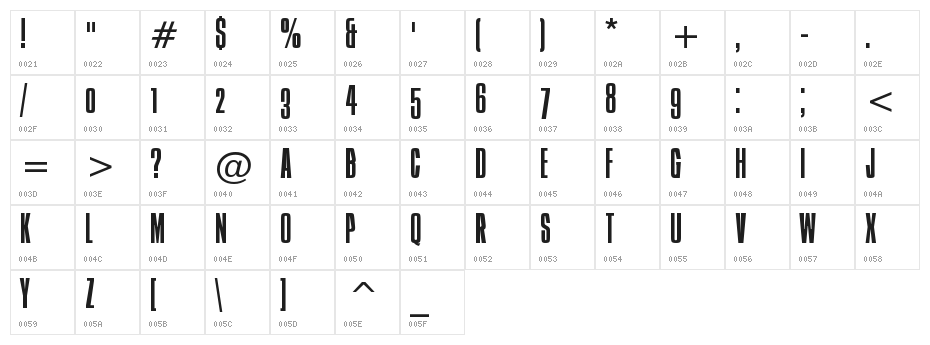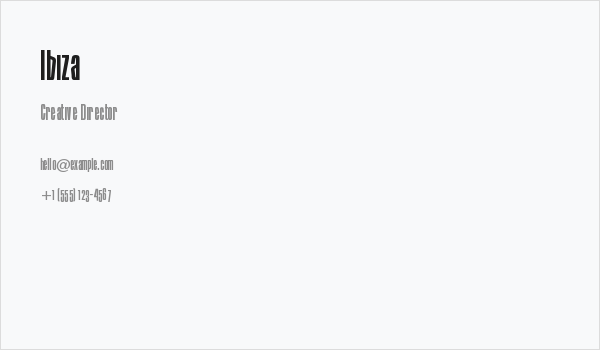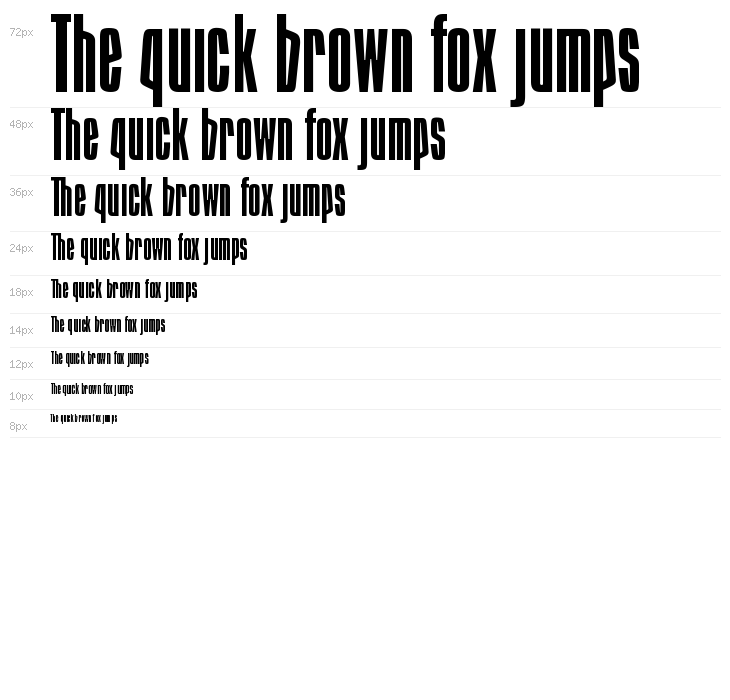
Ibiza Font
| Proyectos propuestos | This font is perfect for projects that require a strong visual impact, such as posters, headlines, branding, and advertising materials. Its bold nature makes it suitable for conveying messages with authority and style. |